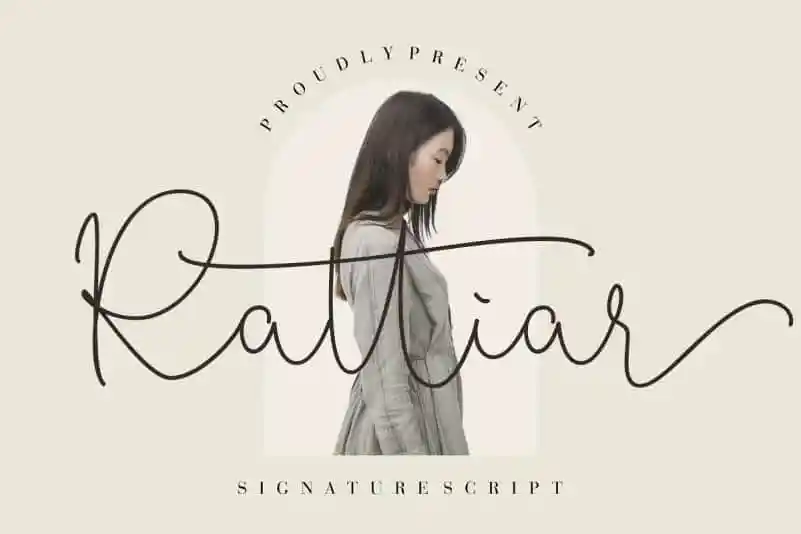
Rattiar Handwritten Font – Download Grátis
A Rattiar Handwritten Font é uma elegante fonte feita para designers que buscam uma mão escrita sofisticada. Criada pela Creatype Studio, essa fonte incorpora um estilo de linhas simples (monoline). Sua principal característica é o uso de “swashes”, ou finalizações elaboradas nos caracteres, proporcionando um toque feminino e delicado às suas criações. Seja para aplicações online ou em impressões físicas, a Rattiar Handwritten Font oferece a perfeita combinação de estilo sofisticado com uma personalidade suave e única. Ela é especialmente atraente para designers que procuram trazer um toque delicado às suas obras, tornando-a um excelente recurso em sua coleção de fontes. Não importa o tipo de projeto, essa fonte irá fazer dele algo impecável.